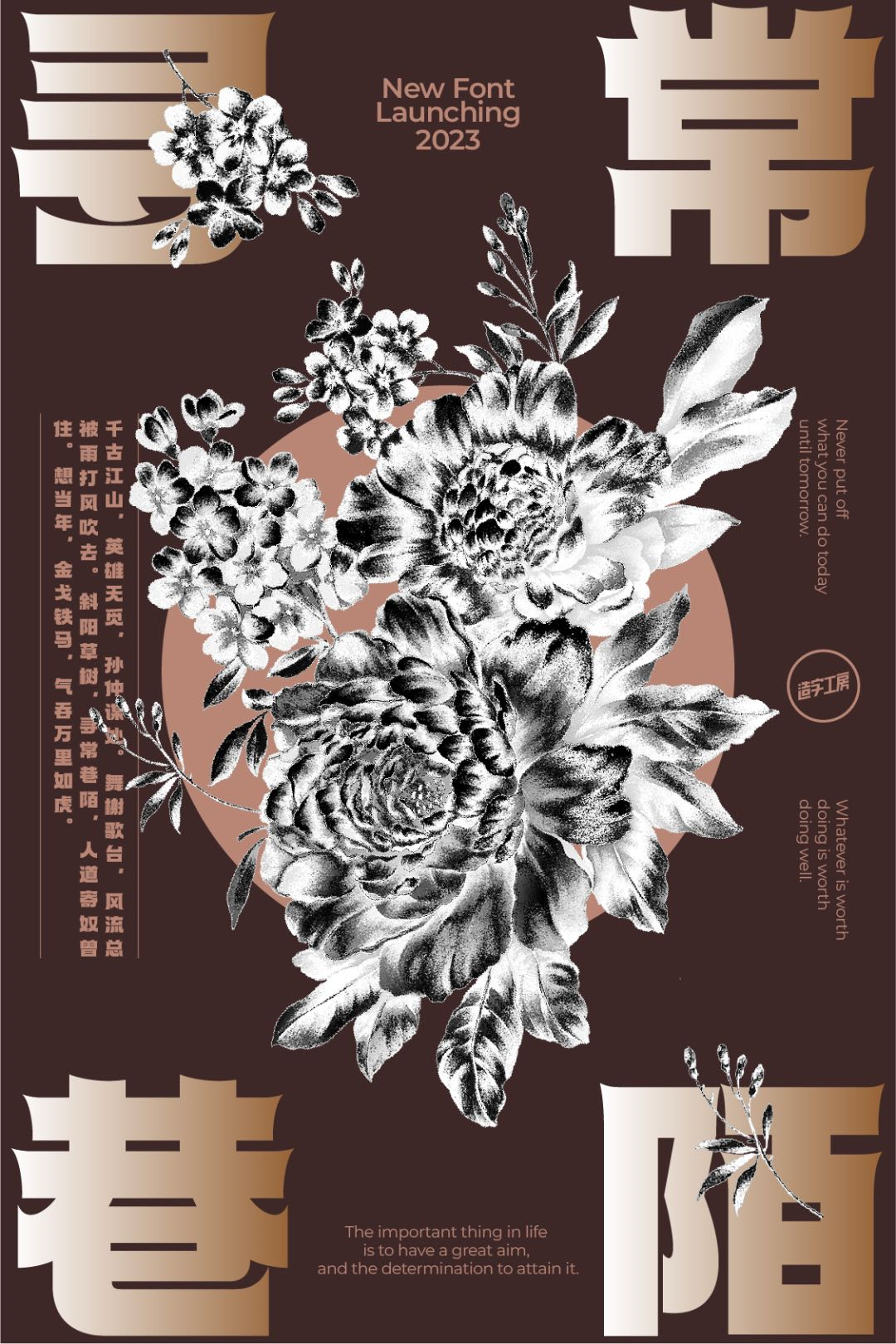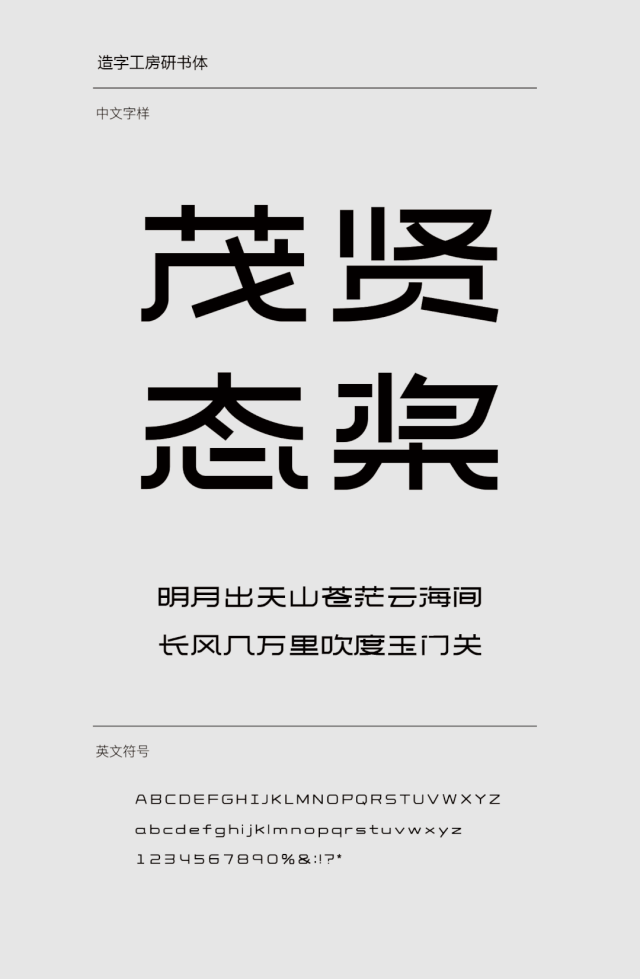
砥砺造字,新体上市!造字工房2023年全新字体今日发布
砥砺造字,新体上市!造字工房2023年全新字体今日发布 疫情三年,在一次次封控和病毒防御中,造字工房的每一位同事都坚守职责,从始至终齐心协力,每一年都坚持将一款款全新的字体产品在这个时期呈现给大家。而今日发布上新的这二十款字体,重疫期间,大多同事在身体严重不适的情况下,为新字体的创作和发布坚持筹备,则尤其珍贵和不凡!相信在以后的每一份应用中,都能带给更多品牌视觉形象上的一丝温情与勇敢。
砥砺造字,我们始终把握自身设计语言,保持原创,拒绝平庸,更抗拒哗众取宠。一年一年,使更多全新字体产品如期而至。我们也以独有的创作风格与节奏,为中国汉字字体产品库的丰富性增砖添瓦,为大众品牌视觉需求的多样性选择而努力创新。
【全新美术字体类】
一、造字工房宾果体
二、造字工房春赋体
三、造字工房沐川体
四、造字工房苍舟体
五、造字工房行秋体
六、造字工房凌岩体
七、造字工房研书体
八、造字工房速写体
九、造字工房锦竹体
十、造字工房美佳体
十一、造字工房云裳体
十二、造字工房吟宋体
十三、造字工房竹黑体系列
十四、造字工房致尚体
【全新手绘字体类】
一、造字工房薄荷海盐体砥砺造字,新体上市!造字工房2023年全新字体今日发布
二、造字工房知夏森林体砥砺造字,新体上市!造字工房2023年全新字体今日发布
三、造字工房芝士少女体
四、造字工房元气泡泡体